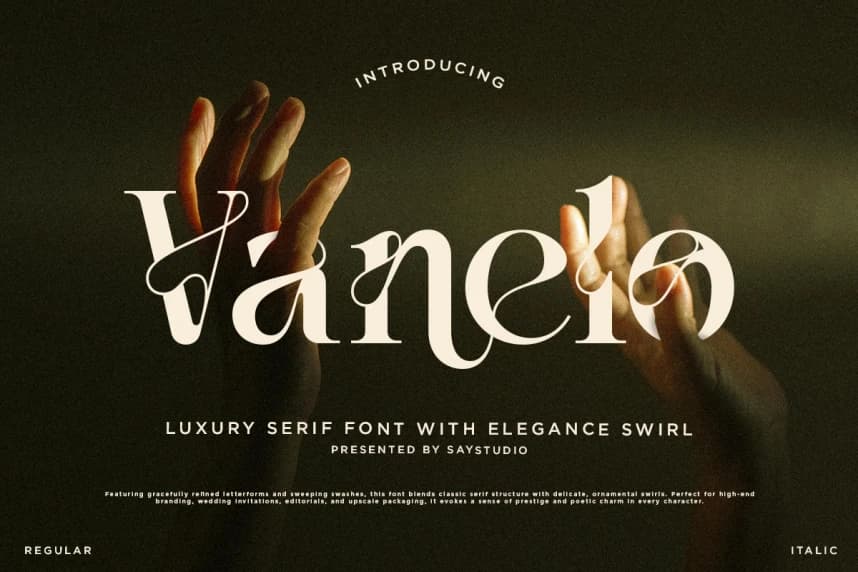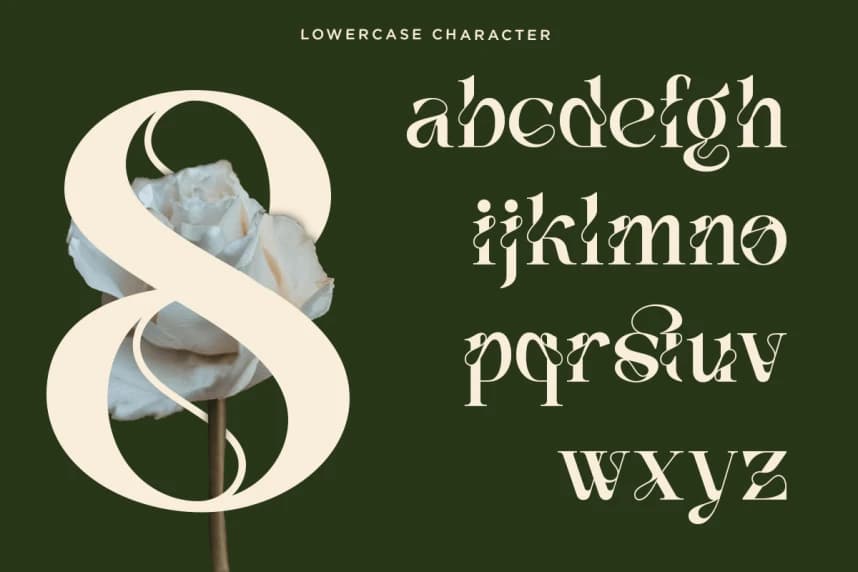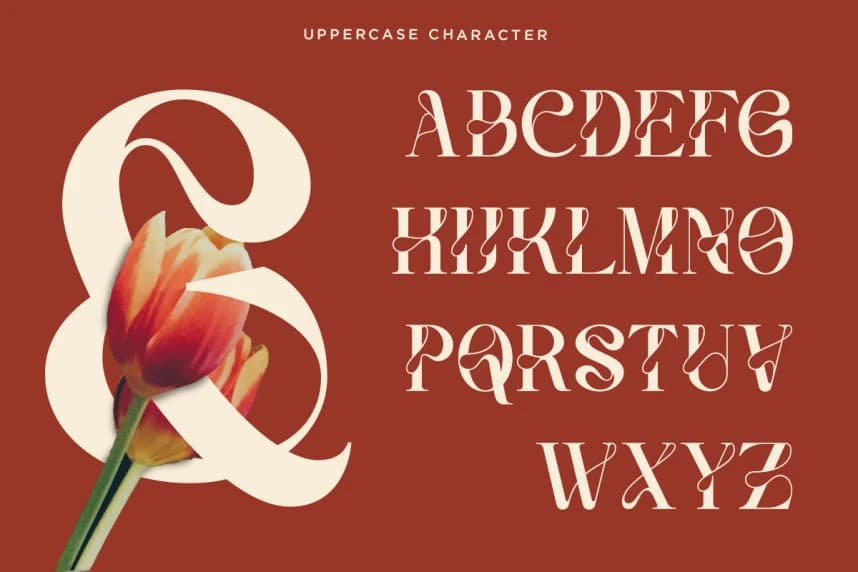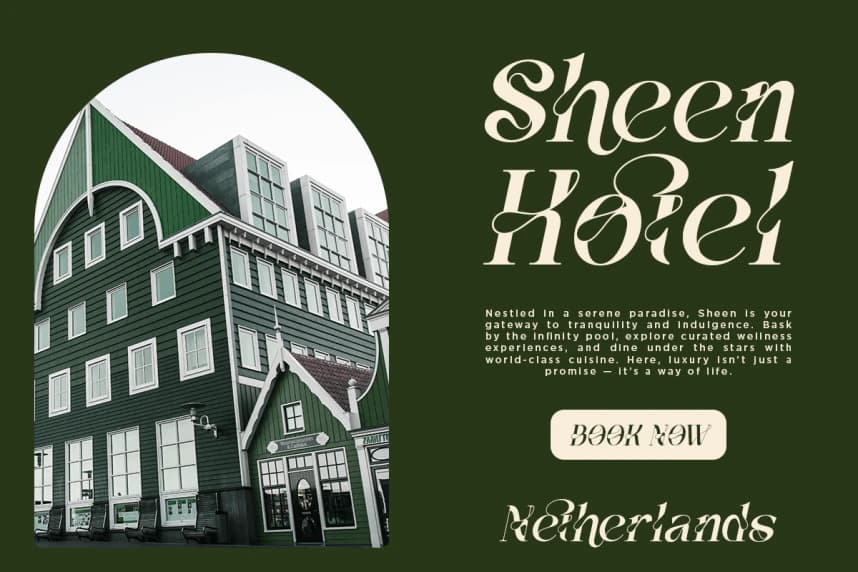
Vanelo DEMO Font
Vanelo DEMO Font, dramatik eğrileri minimalist zarafetle birleştiren lüks bir serif yazı tipidir. Moda editörlükleri için, premium ürünlerin markalaşması ve zarif logolar için tasarlanmıştır; Vanelo, bir gizem ve zamansız güzellik havası taşır.
Vanelo DEMO Font, zarif kıvrımlarla dramatik eğrileri minimalist zarafetle birleştiren lüks bir serif yazı tipidir. Moda editörlükleri için, premium ürünlerin marka tasarımı ve zarif logolar için tasarlanmıştır; Vanelo gizemli bir aura ve zamansız güzellik taşır.